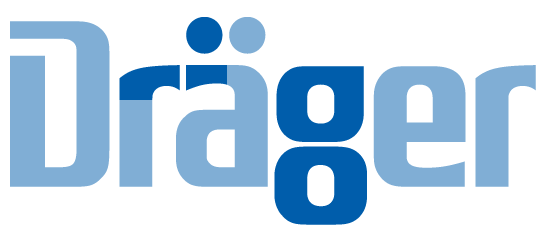
Das lustige Sommerloch-Ratespiel 2009
Man schätzt die Produkte des Unternehmens – mit Sitz in Köln – wegen ihrer hohen Qualität. Die Produkte sind auch nicht ganz billig. Ihr Design macht sie allerdings unverwechselbar. Und Product Placement ist ein bevorzugtes Marketing-Instrument des Herstellers. Na?
Mir ist dieses Logo in der Vergangenheit schonmal im Zusammenhang mit Koffern ins Auge gesprungen. Rundschrift plus Umrandung trifft man in dieser Form nicht all zu oft.
Ich versuch’s derweil mal hiermit:
Das Unternehmen ist in der Kommunikationsbranche angesiedelt und noch recht jung.
Kannst auch gleich noch die Überarbeitung der Texte anbieten.
Zu einem ihrer Koffer schreiben sie:
»Wer mit einem Gepäckstück aus der neuen Topas Titanium-Serie unterwegs ist, kann sich auf den Neid seiner Mitreisenden freuen. …«
Das macht doch richtig Lust, sich ein RIMOWA-Teil zu kaufen! Unglaublich.
... und noch recht jung.
Kennt mans denn schon?
Geb doch noch ein paar Hinweise o. weitere Ausschnitte
Das Unternehmen selbst existierte bereits seit Ende der 40er, später als Teil eines Kombinates. 1992 wurde es als GmbH neugegründet und 2000 mit einem weiteren Betrieb fusioniert und in eine AG umgewandelt.
Das ist die Funkwerk AG
Gesucht ist ein deutsches Unternehmen aus dem Norden, das vor mehr als hundert Jahren gegründet worden ist und noch immer aktiv ist. Ein Ausschnitt aus seinem Logo sieht folgendermaßen aus:
Hier also noch ein Ausschnitt. Er ist grenzt nicht an den ersten an. Es handelt sich um einen Ausschnitt aus dem Namen des Unternehmens. Dargestellt ist ein Kleinbuchstabe.
Jeder der schon einmal operiert worden ist, ist wahrscheinlich bereits in Kontakt mit den Produkten dieser Firma gekommen, so, mehr wird aber erstmal nicht verraten.
... ich habe den Eindruck, dass im letzten Jahr mehr Leute mitgerätselt haben. Wahrscheinlich wurden sie vom Sommerloch verschluckt ... ;-)
Mein neues Logo kennt jeder. Die Gesellschaft wurde vor fast 100 Jahren gegründet ...
und so alt sieht das Logo auch fast aus. Es handelt sich um eine Wort-/Bildmarke.
Hmmm, dann werfe ich mal dies hier in den Ring:
Produktmarke eines deutschen Traditionsunternehmens. Das Produkt ist mit dem, was es kann, ziemlich allein auf weiter Flur. Ist manchmal die letzte Rettung …
... ich würde jetzt ja sofort »Original Dr. Beckmann Fleckenteufel« rufen, weil die ja in mintgrünen Fläschchen daherkommen – aber ich erkenne das Logo nicht. Also rufe ich lieber mal nicht ...
Du weißt doch, wie das „grün-grün-grün“-Lied weitergeht?
Blau, blau, blau, …, rot, rot, rot, …
Es geht nicht um eine bestimmte Farbe, sondern eher um Farbe an sich.